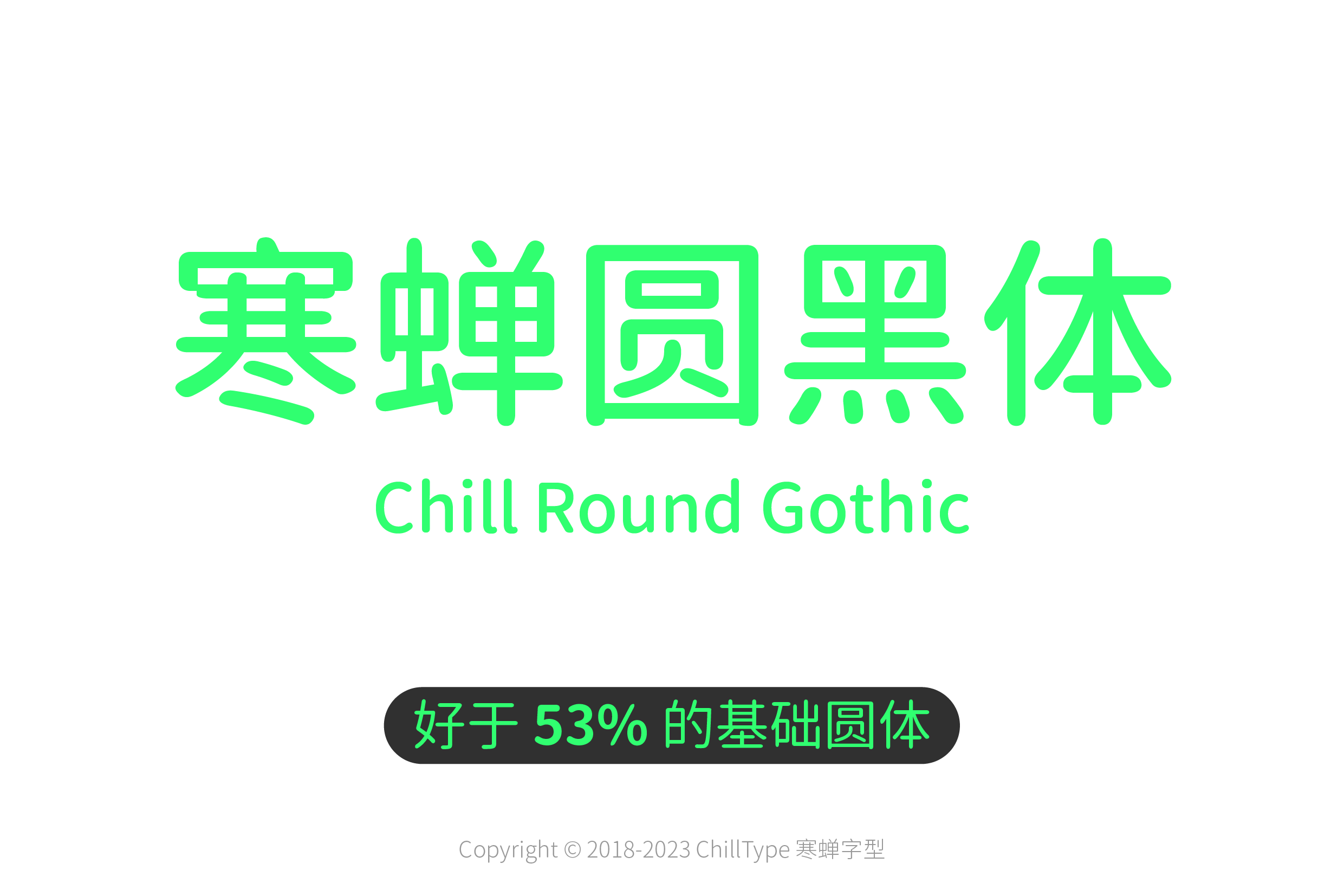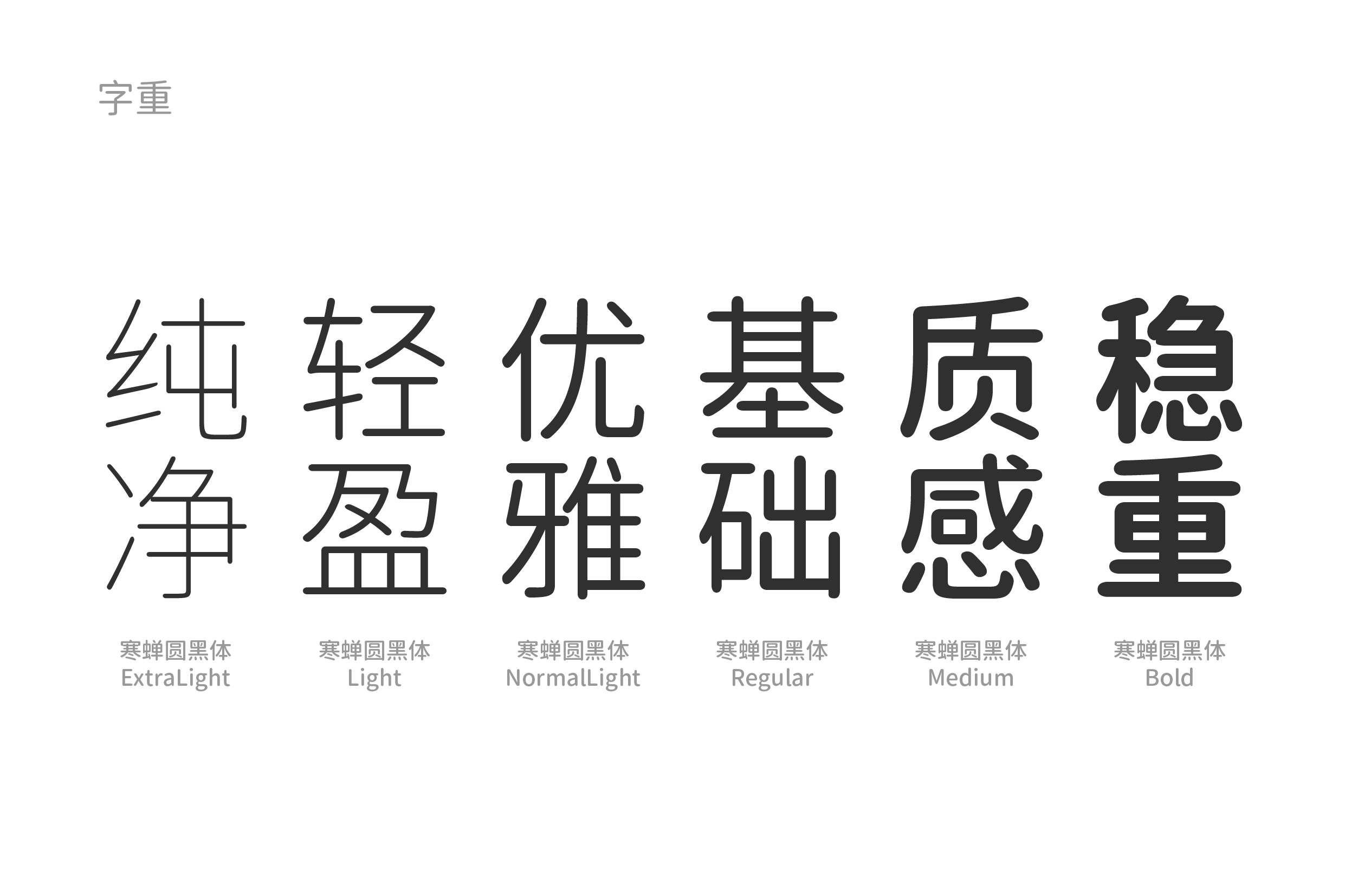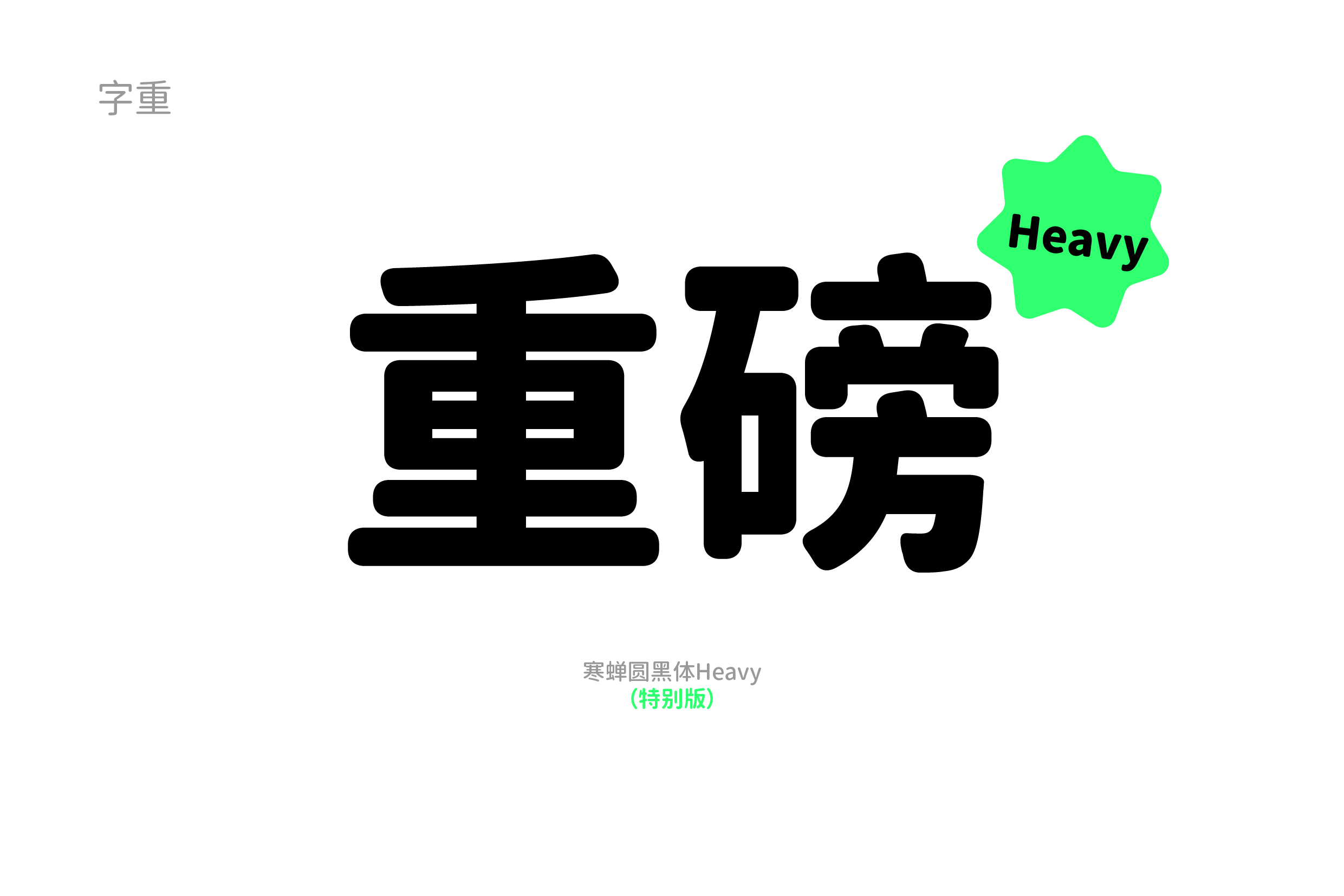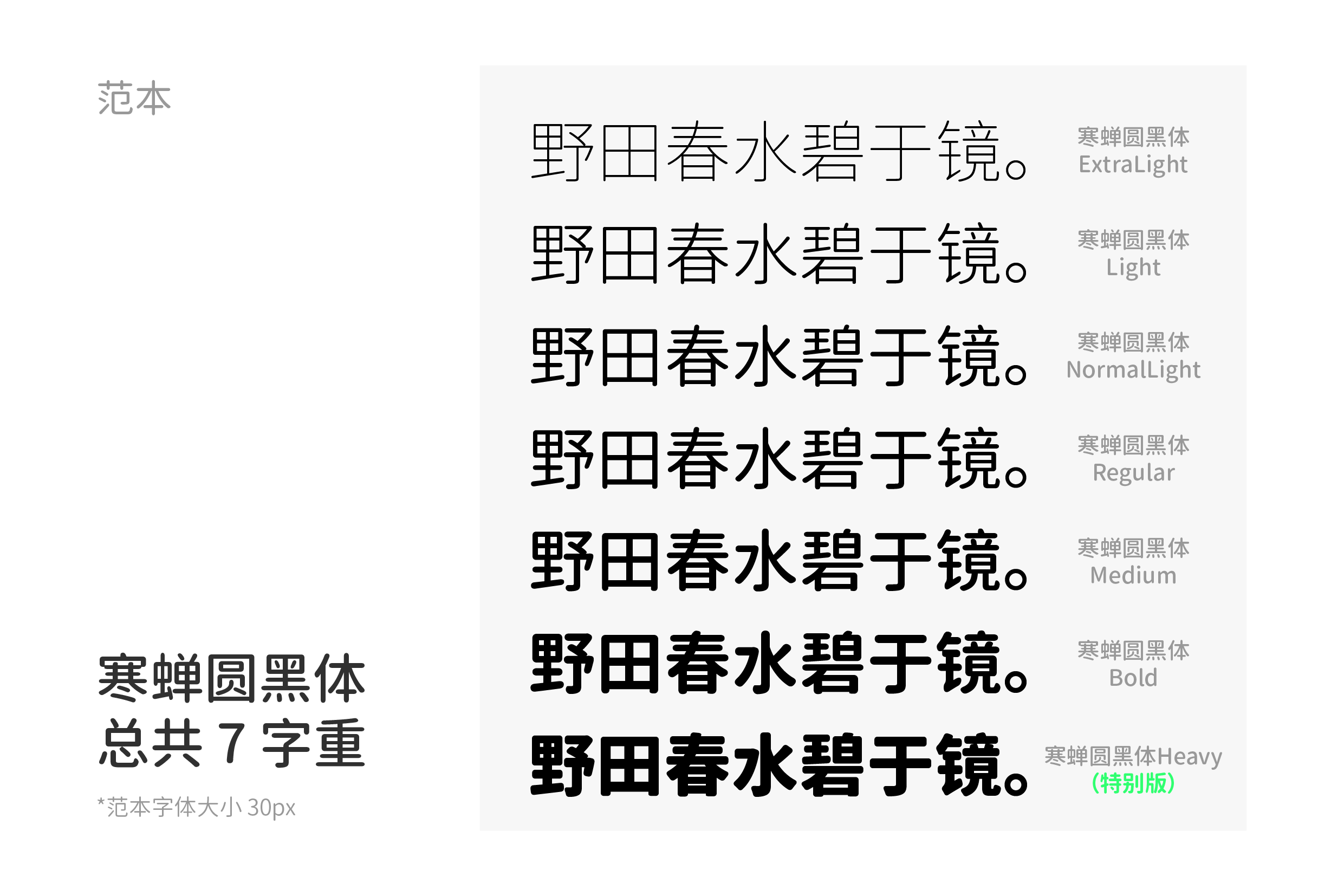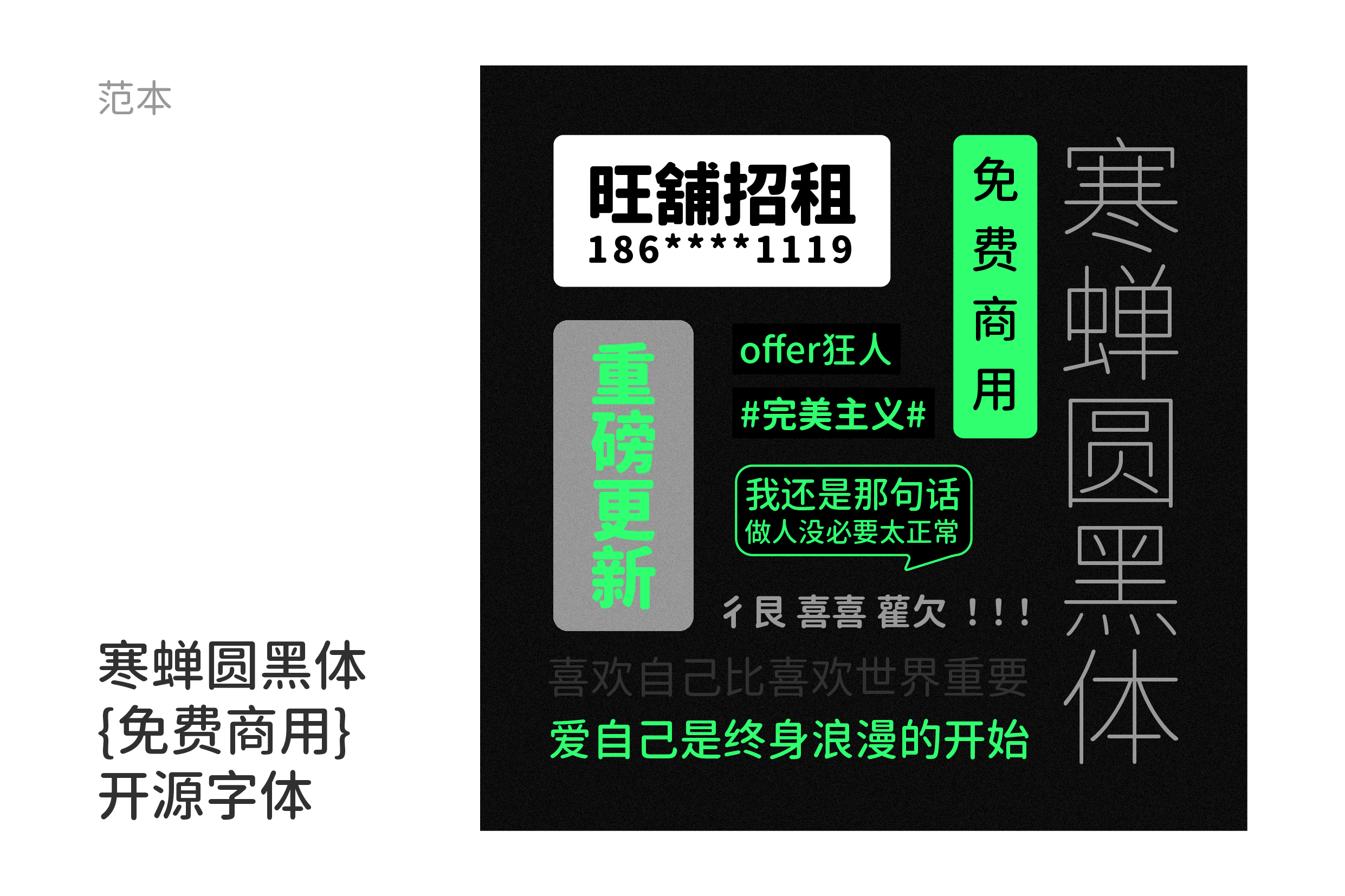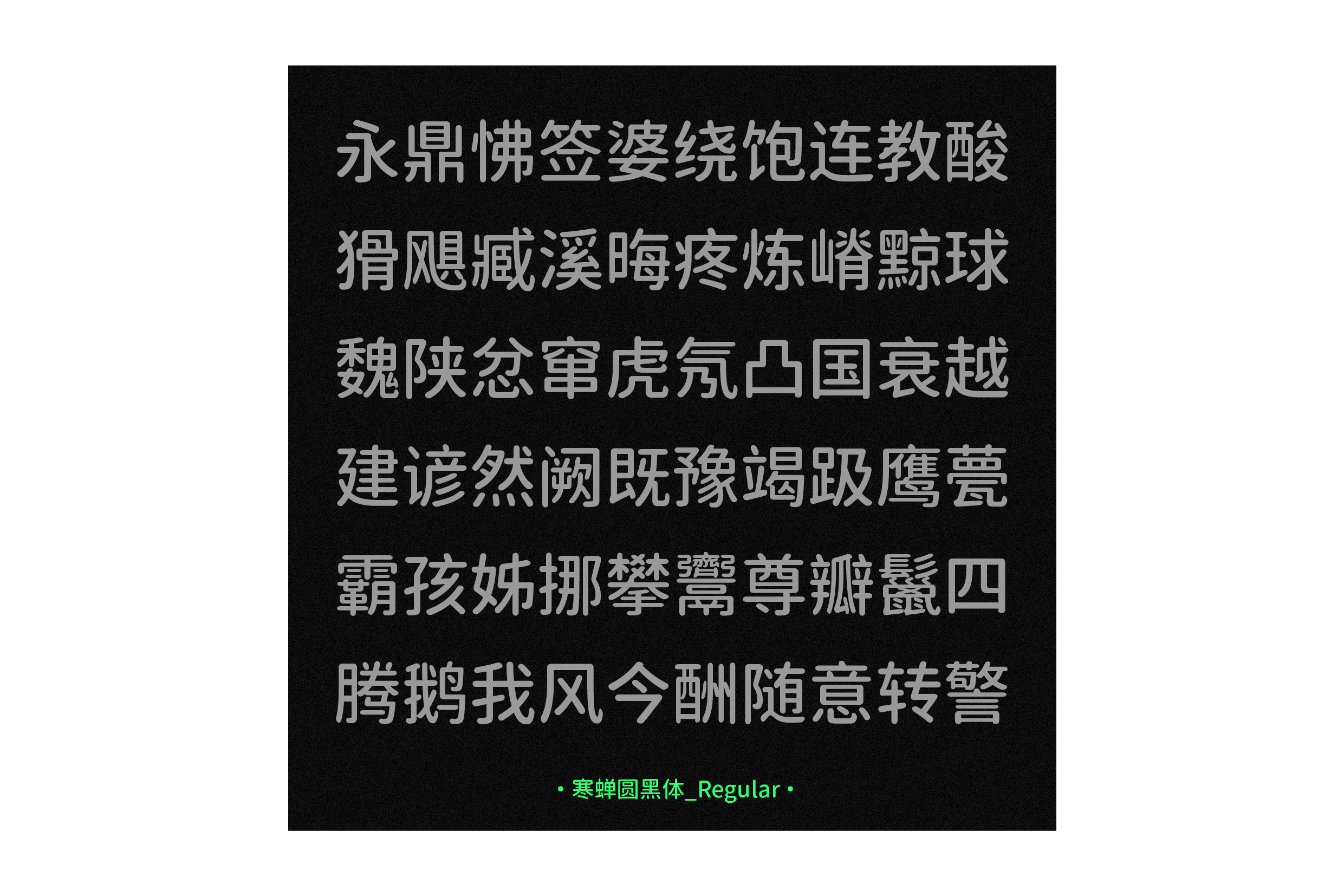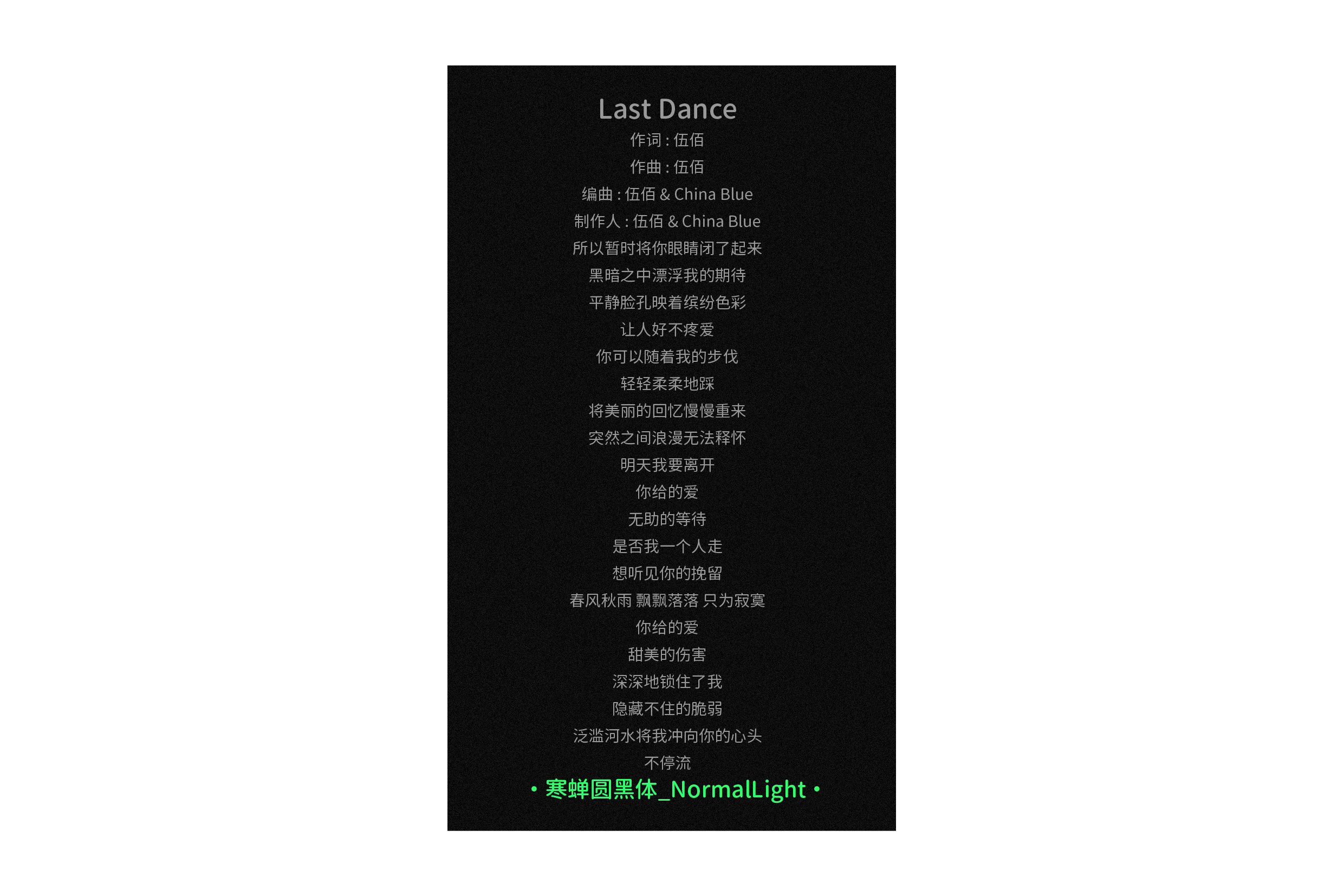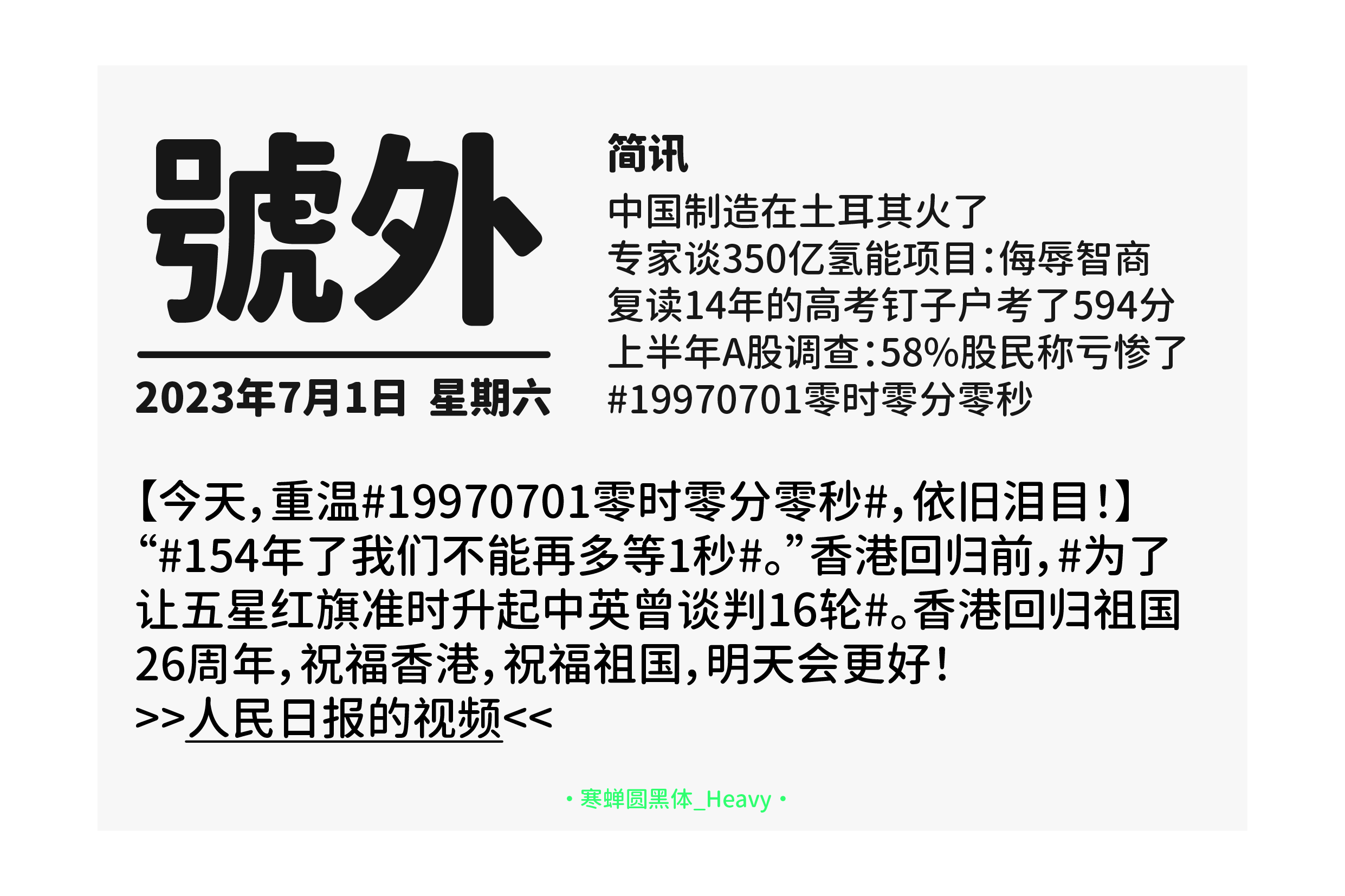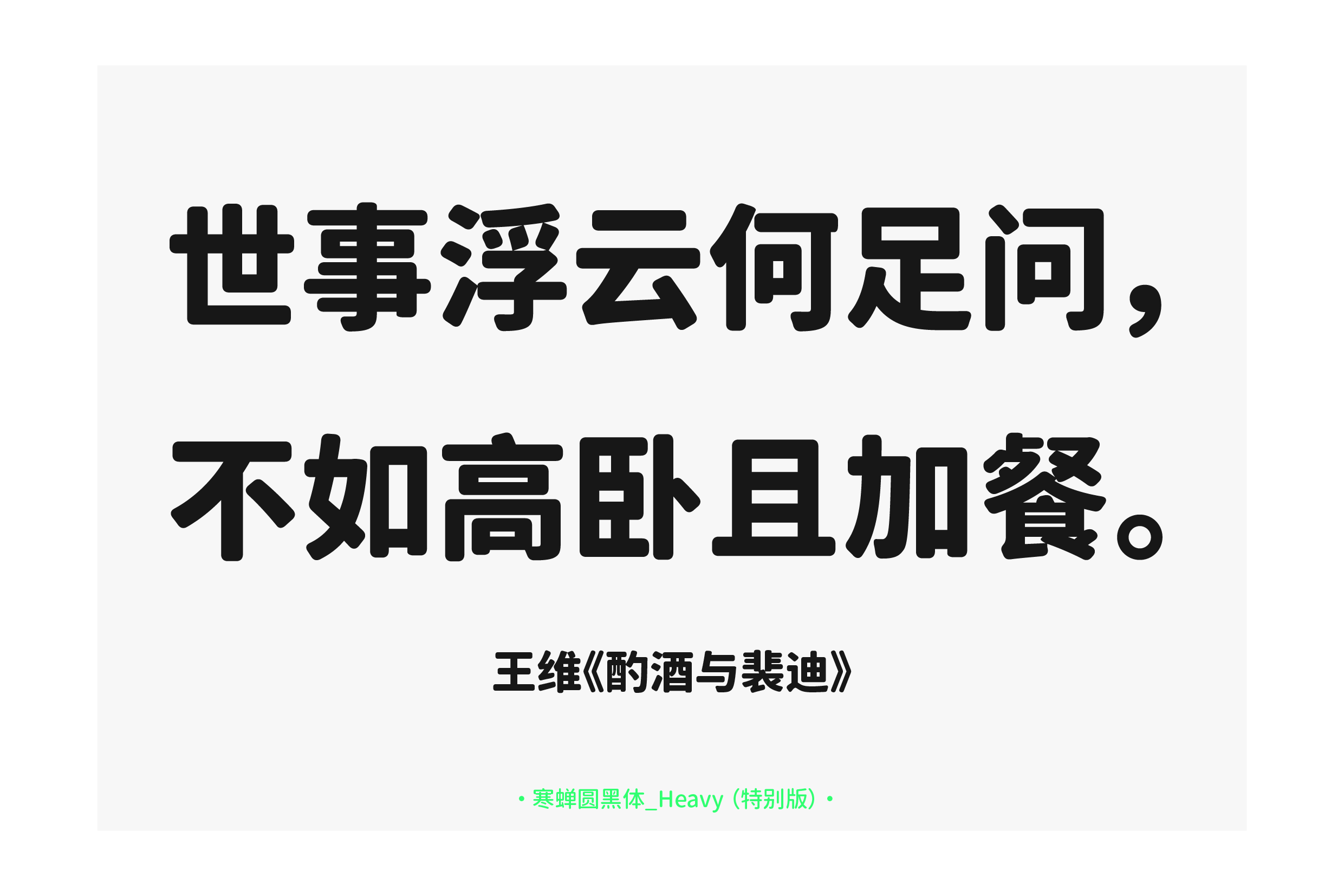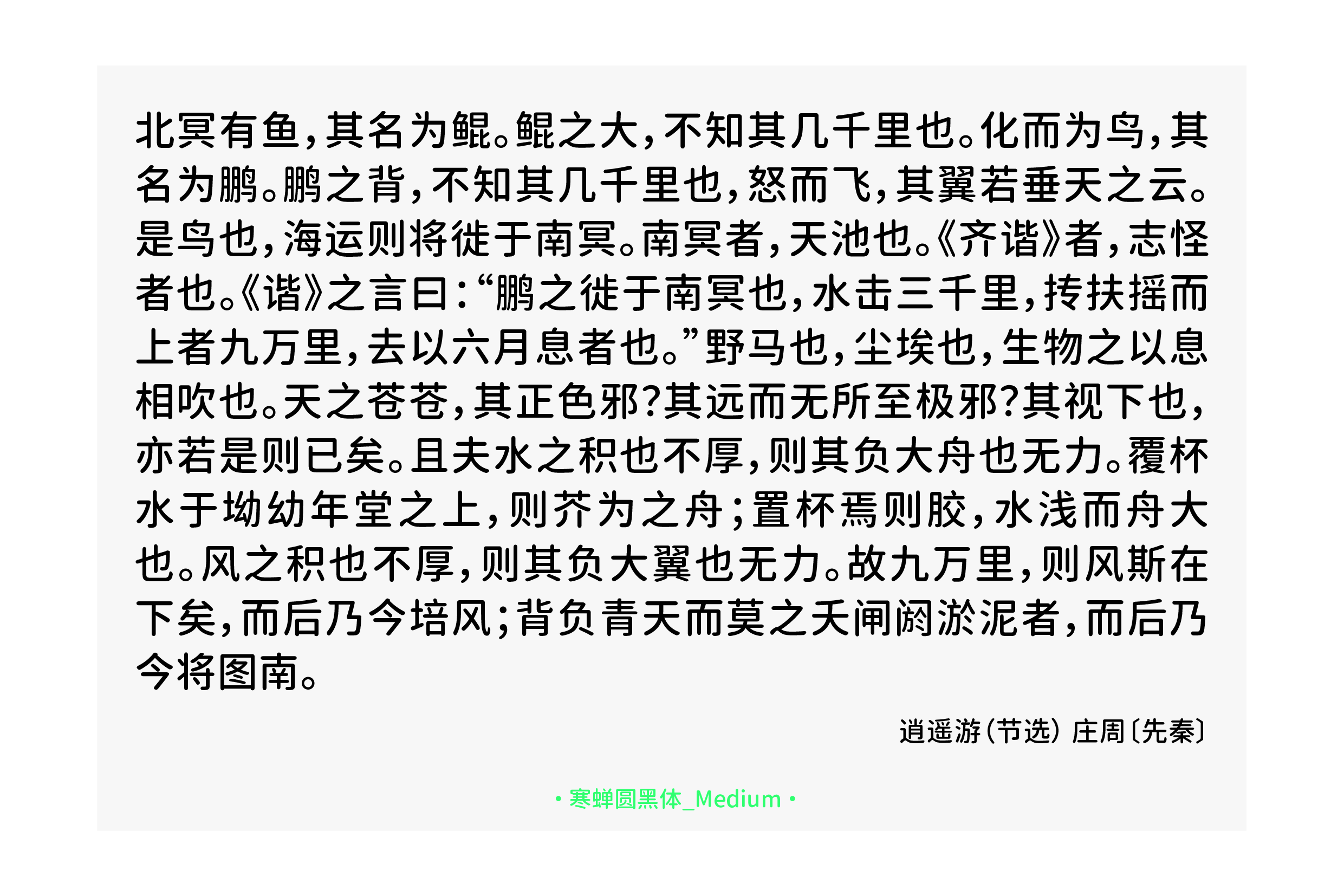
寒蝉圆黑体是一种以思源黑体(Source Han Sans SC)为基础进行圆角化改造的字体。这种设计通过在保留思源黑体原有的结构与清晰度的同时,将笔画的尖锐拐角与末端处理为平滑的圆弧形态,从而显著改变了字体的整体视觉风格。具体而言,设计师在不改变字体骨架和基本比例的前提下,对横、竖、撇、捺等笔画的起笔、收笔以及转折处进行了细致的圆角化处理,使原本锐利的边角变得柔和流畅。 圆角化处理使得字体看起来更加柔和、亲切,有效减少了传统黑体的刚硬感与距离感,营造出温暖、友好的视觉氛围。这种特性使其特别适用于需要传递亲和力与轻松感的应用场景,例如面向儿童或家庭用户的产品界面、强调健康与自然理念的品牌标识,或是社交媒体、教育类应用中的标题与重点文案。此外,在轻量级的阅读场景中,如电子书的副标题或提示性文字,圆黑体也能在保持可读性的同时增添细腻的视觉层次。 这一改造属于典型的风格变体设计,旨在基于成熟且广泛使用的开源字体,进一步扩展其适用场景与艺术表现力。通过圆角化处理,寒蝉圆黑体在保留思源黑体优秀的多语言支持与屏显适配能力的同时,为设计者提供了更丰富的风格选择,使其能够灵活应对从技术文档到情感化交互等多样化的排版需求。
寒蝉圆黑体字体,好于53%的基础圆体。
展示“寒蝉圆黑体”字体不同字重效果,从ExtraLight到Bold,演示“纯净轻盈优雅基础质感稳重”等字样的笔画粗细变化。
寒蝉圆黑体Heavy(重磅)字重效果示例,右上角有绿色Heavy贴纸,下方标注为特别版。
寒蝉圆黑体字体样本,共展示了从ExtraLight到Heavy的7种字重。
寒蝉圆黑体字体在不同场景中的应用示例,如旺舖招租、社交媒体帖子和励志语句,展示其免费商用特性。
寒蝉圆黑体_Reguar 字体的字符样张,展示了多种汉字。
伍佰歌曲《Last Dance》的歌词文本,包含作词、作曲、编曲、制作人信息与完整歌词,底部标注显示字体为寒蝉圆黑体_NormalLight
號外简讯,包含中国制造在土耳其走红、氢能项目被批、高考钉子户考分、A股股民亏损等新闻标题,以及关于香港回归26周年的纪念文字和人民日报视频链接。
王维《酌酒与裴迪》诗句:世事浮云何足问,不如高卧且加餐。
庄子的《逍遥游》节选,包含关于鲲鹏的寓言故事。
寒蝉圆黑体项目说明,基于思源黑体进行圆角化转换,并手动校准字符集问题。